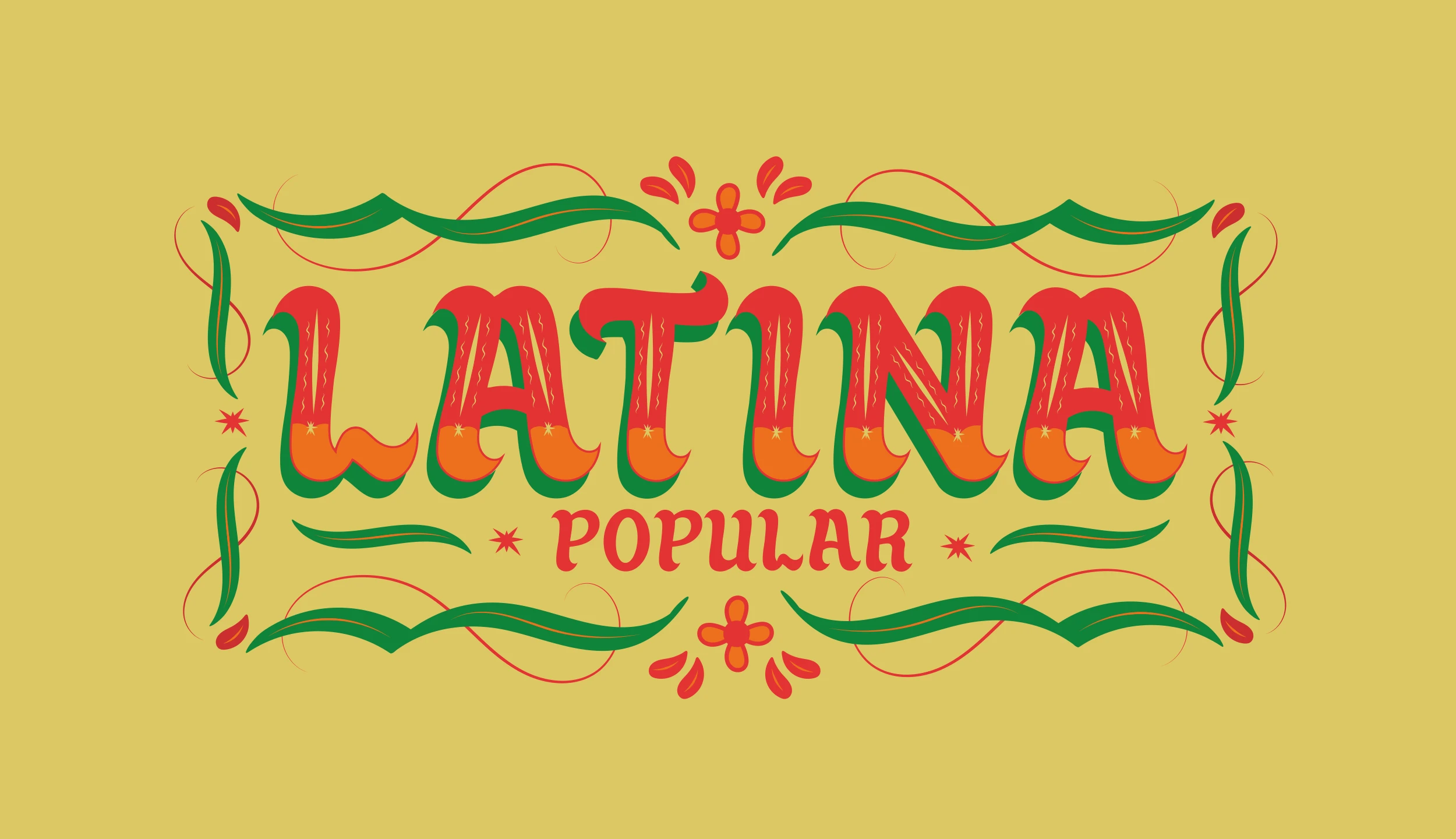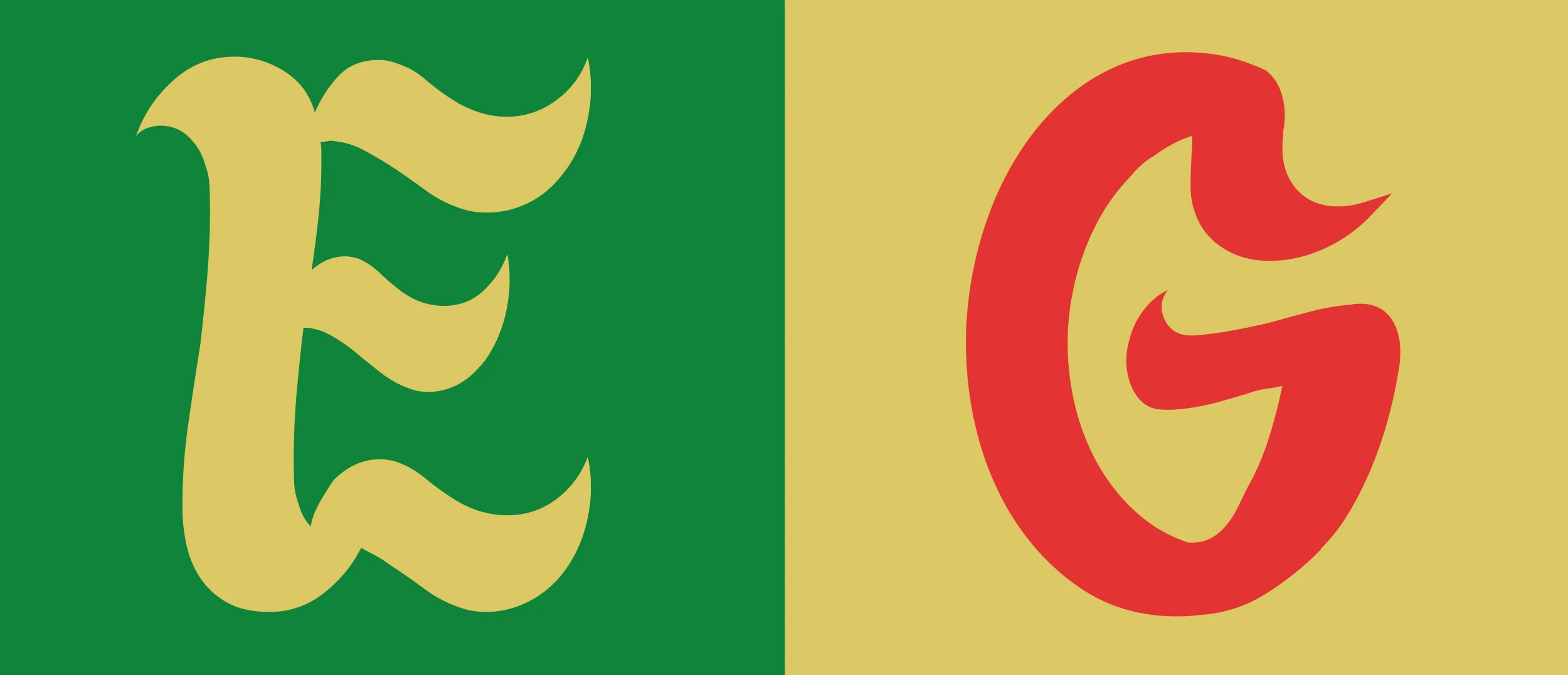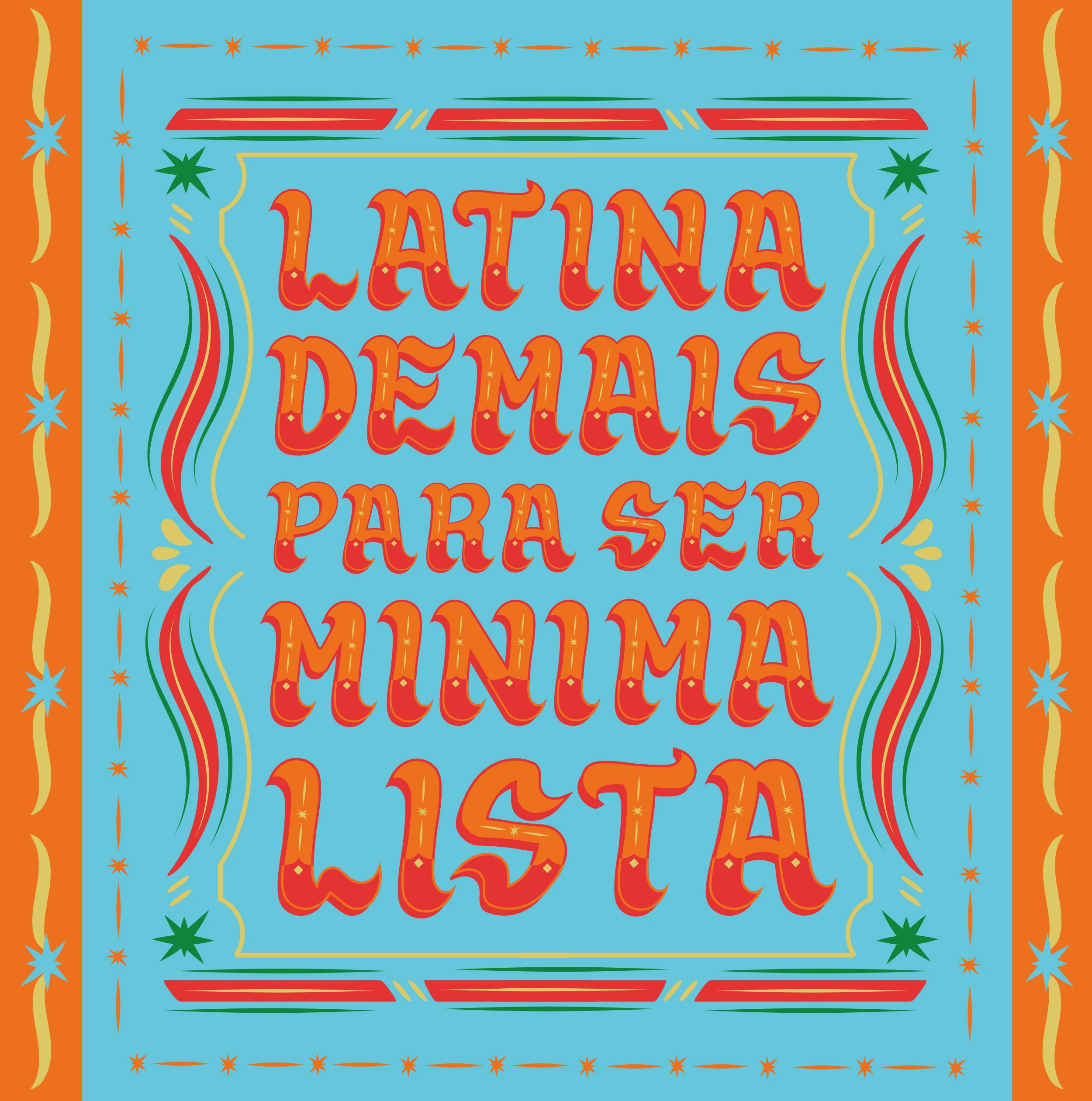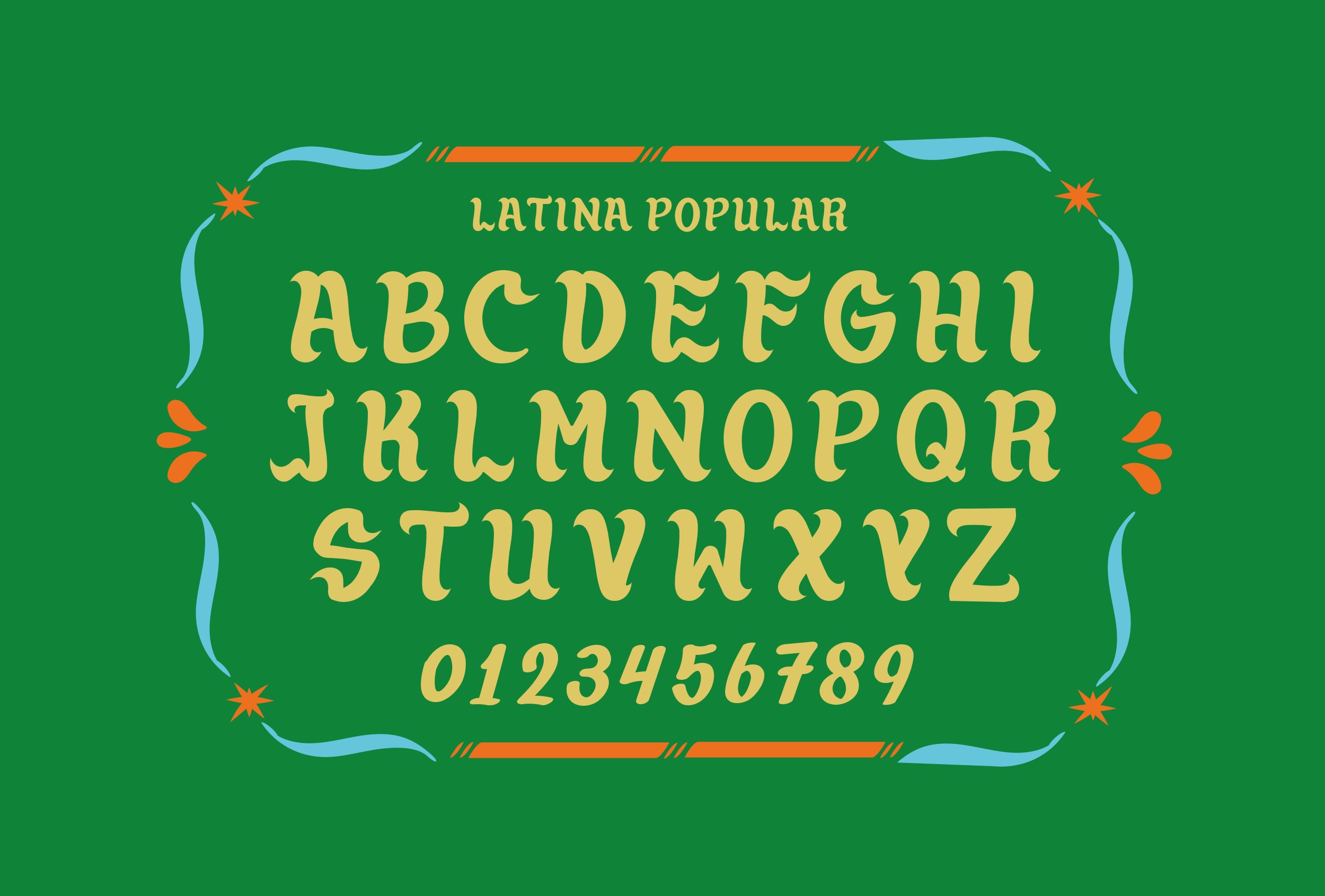
Latina Popular
Latina Popular 是一款充满拉丁美洲地域特色的装饰字体,设计灵感来源于秘鲁街头常见的 Chicha 风格手绘招牌。字体将当地民间招牌中鲜明、热烈而富有装饰性的视觉语言融入字形设计,通过夸张饱满的字母轮廓、流畅的曲线变化以及富有节奏感的造型,让文字呈现出浓厚的街头文化气息与独特的视觉表现力。
Latina Popular 的字形具有明显的复古装饰特征,整体轮廓厚重而圆润,字母之间带有自然的律动感,并通过富有变化的笔画结构强化字体的视觉张力。从展示效果来看,字体并不追求传统字体所强调的严谨与规整,而是更加注重文字本身的装饰性和情绪表达。搭配鲜艳的色彩以及简单的图形装饰后,可以呈现出非常鲜活的拉丁美洲街头招牌效果。
这款字体背后的设计灵感来自秘鲁具有代表性的 Chicha 字体文化。Chicha 招牌广泛存在于当地的商业招牌、音乐宣传以及街头视觉之中,其最大的特点便是大胆的字形、丰富的装饰和强烈的色彩表现。Latina Popular 并非简单复刻传统招牌字样,而是从这种民间字体文化中提取视觉特征,并重新整理为适用于现代设计的数字字体,让具有地域特色的拉丁字体语言能够以更加直接的方式进入当代视觉设计。
在实际设计中,Latina Popular 更适合用于需要突出视觉个性的场景,例如海报标题、音乐视觉、餐饮品牌、包装设计、活动宣传、服装图案以及街头文化相关设计等。尤其是在复古、热烈、自由或者具有浓郁地域文化气息的主题中,字体本身就能够成为画面中的重要视觉元素。相比普通的英文字体,Latina Popular 更强调文字的图形属性,短标题或品牌名称经过排版后能够形成较强的视觉识别度。
Latina Popular 免费提供个人及商业用途使用。 对于正在寻找复古装饰风格、拉丁美洲文化特色或街头招牌视觉的设计师来说,这是一款非常适合用于标题和主视觉设计的字体。它鲜明的字形风格能够快速建立画面的视觉氛围,让简单的文字也拥有更加丰富的表现力。
Latina Popular 的设计也体现了字体与地域文化之间的联系。它没有刻意将民间字体语言进行过度现代化处理,而是保留了 Chicha 招牌文化中自由、夸张和富有生命力的一面。对于设计师而言,这种具有明确文化来源的字体能够提供不同于常见欧美现代字体的视觉选择,也让拉丁美洲丰富的民间字体文化拥有更多进入当代设计的可能。